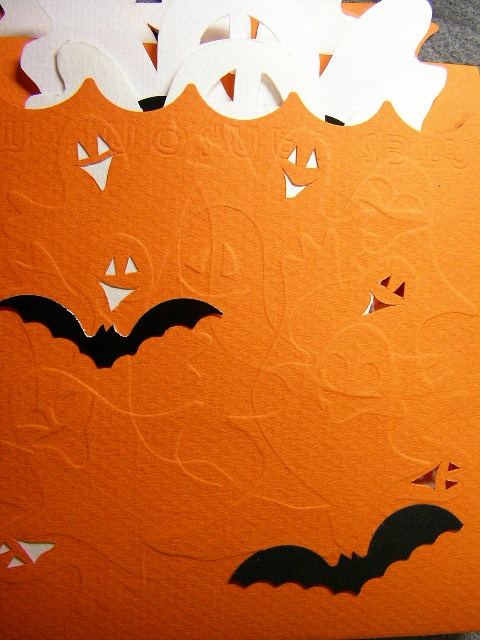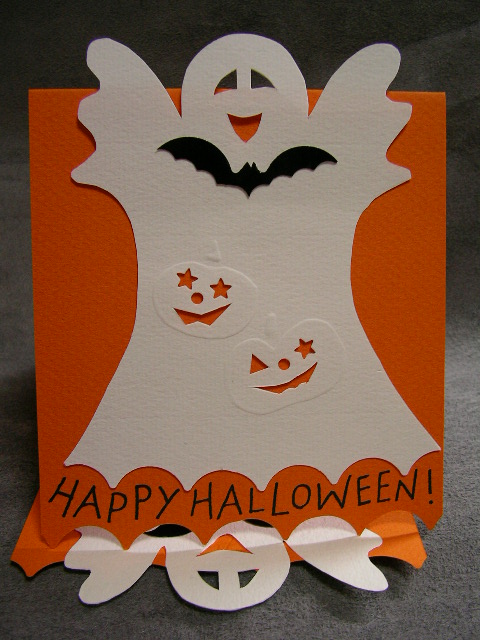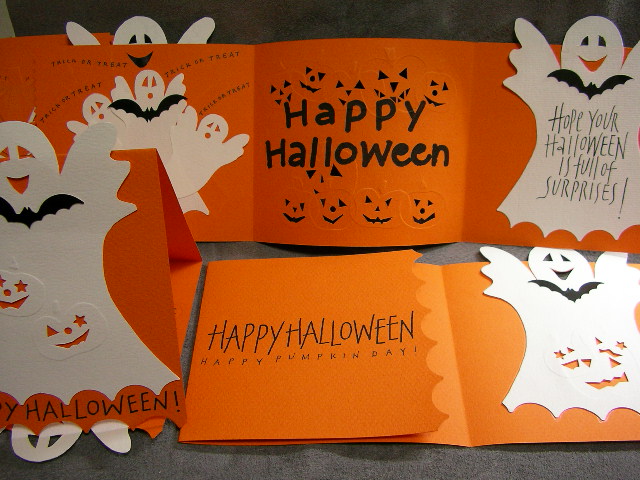
HAPPY HALLOWEEN!
HAPPY HALLOWEEN! 10月の最終日、いよいよHALLOWEENです。ここ何年か盛り上がりを見せるハロウィンデイ!このおかげで、クリスマス前の街にオレンジ色が10月を華やかに彩っています。仮装パーティとまではいきませんが、パンプキンパイは、食べなくっちゃと思う日であります!
さて、クラスでハロウィンのカードを作ったので紹介します。HALLOWEENのキャラクターといえば、カボチャ、オバケ、コウモリ、魔女、黒猫ですが、形が単純なカボチャ、オバケ、コウモリの3種をモチーフにして作りました。オレンジの紙は、キャンソン・ミ・タント、なかなかきれいな色で気にっています。文字は、Bスタイルのペンで書きました。ハンドエンボスのカボチャやオバケがいっぱいです。そして、何年か前に買ったクラフトハサミがやっと日の目をみました。大きなスカラップができるハサミを使って作ったコウモリの形のサンプル見て、ほしくて2種類買った記憶がありますが、さて、いざ使うとなったら、どんなだったか?で、あれこれやってみた結果、小さいスカラップとの組み合わせに落ち着きました。大きなスカラップの間にある小さい山の部分に切り込みをいれたら、よりコウモリらしくなったので、満足!満足!
では、楽しいHALLOWEEN NIGHTを! TRICK OR TREAT!
ふるさと記念館
先日、新潟県の小さな町を車で通った時、こんな奇抜な建物を発見しました。
このあたりは、典型的な日本の田舎の風景が広がる阿賀野川の源流を遡った、新潟と西会津の境目付近です。そこに突然出現する真っ赤な建物。しかも壁にはおかしな形の四角が全面に付いている。一体これは何!?
ここは、新潟県東蒲原郡阿賀町鹿瀬という町のふるさと館です。このあたりには、川をせき止めて出来たダムと 発電所が多くあり、また紙の原料の楮(コウゾ)にも恵まれた地域なのだそうです。そこでこのふるさと館では、電気と和紙をテーマにした展示がしてありま す。体験コーナーもあり、「和紙の灯り」も作れるそうです。奥阿賀 鹿瀬ふるさと館
それにしても、この建物のデザインは奇抜!本当に驚きます。
この外壁レリーフの作者は松宮喜代勝さんで、鹿瀬の月と太陽をイメージして作ったと、入り口に書いてありました。
このデザインで行こう!と決めた町のお役所の方、エライです。気に入りました。
いろいろな形の四角はルーリングペンで書いたようなマークでホント面白い!
以前ご紹介したフンデルトヴァッサーにも似てますね〜。
ボタンのお色直し
洋服を思い切って捨てるとき皆さんボタンはどうしてますか?
ジャケットやコートなどは比較的大きなボタンがついているので、はずしてとっておくことが多いのですが、あまりに溜まると「どうしよう・・・」と悩んでしまいます。
そんな時は溜め込んだボタンを一気にお色直ししてしまいましょう!プラスチックの表面なので、アクリル絵具を使うと色が塗れます。持ちにくい場合は竹串をボタン穴に差し込むと扱いやすいです。乾かすときも楊枝か竹串にさしたまま発泡スチロールに立てるといいです・・・。
一気に塗っておくと何かに使うときに楽ですね。その都度やるのも大変なので・・・。私は製本もやるのでお色直しボタンは活躍します。ラッピングやカードにも使えますね。
こういう作業はみんなでボタンを持ち寄ってワイワイやるのが楽しいと思います。こんなボタン企画をしたら皆さん参加されますか?
ゴールド探検ブック
今回のワークショップは、モジトルメンバーがかき集めた金色の画材43種類を、ひとつのアコーディオンブックにまとめるというものでした。
透明水彩絵の具、ガッシュ、アクリル絵の具、インクなどなど、探してみると本当にいろいろあるんですね。下地に使ったり、その画材を使って文字を書いたり する事が前提なので、適さない物は省きましたが、それでもまだまだ探せばきっと出てくる事でしょう。日本では手に入らない画材も紹介致しました。
文字の書きやすさはきっと人それぞれでしょうが、金色で文字を書くなら、私はやはりschmickeです!その他、画材別使いやすさのまとめもメルマガでご紹介しています。
ブックカバー
ところで本にカバーをかけていますか?私は読むとき邪魔なのでカバーをついとってしまいます。棚に並べて置くときもカバー無しのほうが好き。(でもカバーがあるほうが書名が探しやすいのですよねー)
カバー敬遠派の私ですがこんなふうに文字や色で遊んだカバーをつくるのは好きです。書棚の飾りにもなりますよね。写真は気に入りの詩の本のために書いてみたものです。背のタイトルを書くだけならとってもカンタンです。
バッグに入れる文庫本には不要になったカラーコピーを折ってカバーにしています。(電車内では書名は隠したいので・・・カリグラフィーのこともアピールできるし?) B4サイズの紙を折るのが文庫本にちょうどいいと思います。昔々本屋さんでアルバイトをしていたので実はカバーかけ、得意です。
子ども造形教室合同展「4つの宝箱」
本日は芸術の秋シリーズ二本立てです!
アートは子供達にも夢を広げます。製本教室でご一緒している加賀美さんは子どものための造形教室を開いています。来週皆さんの前にその子ども達の夢 が形になって登場です!子どもの想像力は魅力的!その創造力も素晴らしいのです。いつのまにか忘れてしまった何かを大人の私達に思い出させてくれることで しょう・・・。
ジグマー・ポルケ
上野の森美術館で開催されているジグマー・ポルケ展に行ってきました。
ジグマー・ポルケは、旧東ドイツ生まれの今もっとも注目されている現代美術家だそうです。今回の展覧会は日本におけるドイツ年の行事の一環で、日本における初の個展だそうです。
「種々の素材とテクニックを自由に駆使しながら、日常生活から童話、歴史、戦争にいたるさまざまなモチーフを画中に取り込 み、豊かなイメージを紡ぎ出す“絵画の錬金術師”ジグマー・ポルケの世界」だそうで、代表作の不思議の国のアリスは、プリント生地の上にドットで描かれて いて、とても独創的です。巨大なキャンバスに数字とそれを結ぶ線が描かれた魔法陣シリーズも不思議な世界でした。画像で見るより、実際に見た方がその大きさと質感を楽しめると思います。
ミュージアムショップに置いてあるドイツのアーティストの本も面白いかったですよ。
ウォーターフォード 水彩紙
カリグラフィーに適した紙はいろいろありますが、皆さんはどんな紙がお好きですか?
ペンで書くのを前提に考えると、ホットプレス(極細or細目)がやはり書きやすいですよね。
一番ポピュラーなのはやはりアルシュの極細ですが、少々お値段がお高い・・・・。ファブリアーノも素晴らしい紙ですが、こちらもどんどん使うにはちょっとおサイフと相談しないとなりません。(ファブリアーノ5ならいいかもしれません!)
画像の紙はSaunders(ソーンダース)のWaterford(ウォーターッフォード)と いう水彩紙です。細目の190gでお値段は500円と、他に比べると少しリーズナブルな紙です。色はホワイトで少し表面が柔らかめ、どちらかと言うとワッ トマンに似ています。水彩絵の具の発色も良いし、ペンの滑りがよいけれどある程度引っかかりもあるので書きやすいです。細いHair lineも出ます。
実はこの紙、イギリスのEwan Claytonによるとヨーロッパではカリグラフィーに関してアルシュホットプレス、ファブリアーノ5と並び近年とても人気がある紙らしいですよ。
日本では新宿の世界堂本店で販売されています。190g500円、300g750円、425g1100円です。メンバーだったらもっとお安く購入出来ますね!
何かいい紙ないかしら?とお探しの方、どうぞお試しください。
シャルルマーニュの暗号
ZERROご存知シャルルマーニュ(日本ではカール大帝)は、西暦800年にローマ教皇から西ローマ皇帝の称号を得たフランク王国カロリング王朝の王で、アルクインなど学者を集めてカロリンジャン書体の統一をすすめ、カロリングルネサンスを推進した、書体の歴史の中でも重要な位置を占める人物です。
そのシャルルマーニュ作と言われる暗号を見つけました!
これは松田行正さんの「Zerro」という本に載っています。形の面白さを持つ記号群(記号、暗号、符号、文字など)総数121項を欧文に限らず世界中から集めてきて紹介している本です。怪しいものから奇妙なものまで、本当に面白い!この本を見ていたら何時間でも飽きずにながめていられます。
この暗号は「単アルファベット換字暗号」で、要するに1つの文字に1つの形を当てはめている作り方だそうで、15世紀になって2つの暗号アルファベットを1文字ずつ交互に適応してひとつの暗号を作る「多アルファベット換字暗号」が生み出されるまで使われていたそうです。
松田さんは一体どこからこの暗号をみつけて来られたのでしょう・・・・・
ちなみにこの本は装丁も変わっています。私が購入したのは黄色ですが、色は何色かあったようでした。本当におすすめの本ですよ!
ミニなカード
先週ミニブックの
お話が続きました
が、それを見て生徒
の美保さんが作った
のが、この可愛い
ミニカードです。
ナント作り方まで書いた紙が入っていて、しかもねじって留める(コレなんて
言うんでしょう)ものまで付いてます。ウサギとくま?の顔もニコニコ、いい
味出していて、お誕生日に頂いたらハッピーになる事間違いなし! 気に入り
ました!ちなみにサイズは、高さ2センチのミニミニです。
このねじねじするものは、いろいろ可愛い柄で売っているそうです。カードに
使うという発想がないと、お店で見ていても目にとまらないのですね。今度見
つけたらゼッタイにゲットせねば!